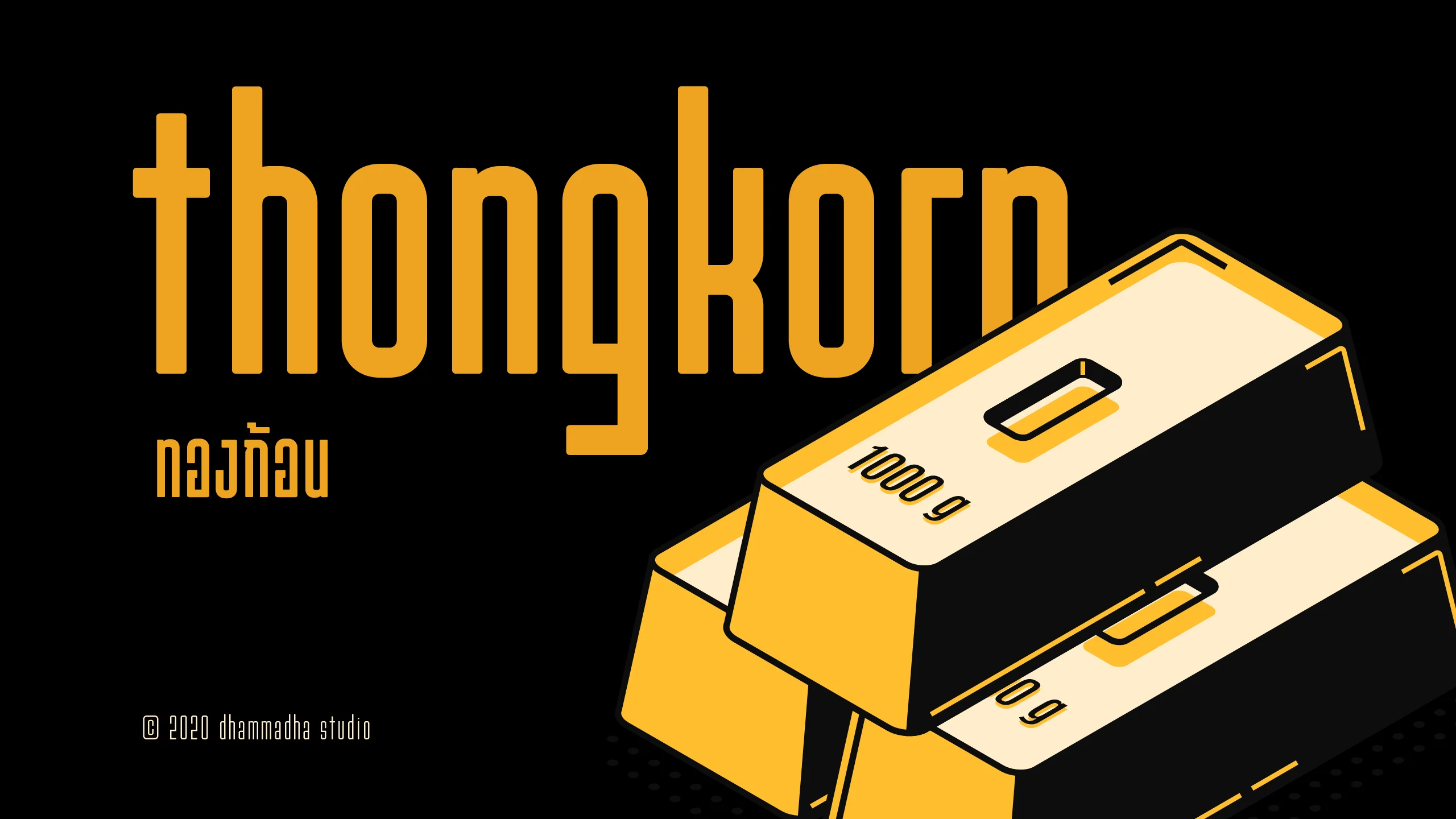
thongkorn
"ทองก้อน | thongkorn" คือชุดอักษรทรงสูงที่ถูกออกแบบมาเพื่อสร้างความโดดเด่นและเพิ่มประสิทธิภาพในการสื่อสารอย่างสูงสุด โดยมีจุดเด่นอยู่ที่ความหลากหลายของน้ำหนักที่ครอบคลุมตั้งแต่ลายเส้นผอมบางไปจนถึงรูปลักษณ์ที่อ้วนตันและหนักแน่น ด้วยโครงสร้างตัวอักษรที่เน้นความกระชับในแนวตั้ง ทำให้ฟอนต์ชุดนี้สามารถบรรจุข้อความและเรื่องราวได้มากขึ้นในพื้นที่ที่จำกัด แต่ยังคงไว้ซึ่งความสวยงามและจังหวะการอ่านที่สบายตา สะท้อนถึงความฉลาดในการเลือกใช้พื้นที่และการสื่อสารอย่างตรงไปตรงมา ด้วยลักษณะพิเศษที่ช่วยประหยัดพื้นที่การใช้งาน "ทองก้อน | thongkorn" จึงเป็นเครื่องมือชิ้นสำคัญสำหรับงานออกแบบที่ต้องการความคุ้มค่าและทรงพลัง ไม่ว่าจะเป็นการทำพาดหัวบนสื่อออนไลน์ที่ต้องแข่งกับเวลา การออกแบบบรรจุภัณฑ์ที่มีพื้นที่จำกัด หรือการจัดวางเนื้อหาในงานกราฟิกที่ต้องการความทันสมัยและดูเป็นระเบียบ ฟอนต์ชุดนี้จะช่วยให้คุณบริหารจัดการพื้นที่ดีไซน์ได้อย่างมืออาชีพ พร้อมยกระดับการนำเสนอข้อมูลให้ดูโดดเด่นและเข้าถึงกลุ่มเป้าหมายได้อย่างชัดเจนในทุกมิติ